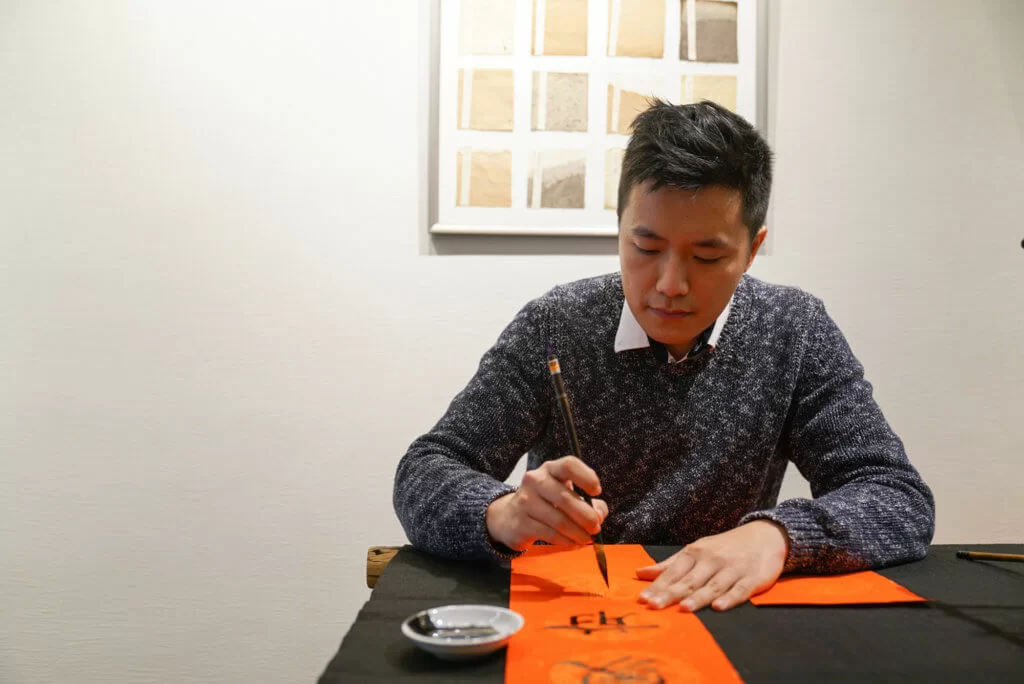
臨近新歲,家家戶戶也會在門前貼上各式賀年揮春。大家可曾心動過想揮毫撥墨寫出自己專屬的揮春?即使大家如筆者打從小學後已把毛筆擱下,書法已見生疏,其實也可以嘗試發揮創意,以畫揉合書法,寫出輕易上手的可愛「福豬揮春」。
準備好紙筆墨,就可安坐在案前,跟着影片示範動起筆來!明周今天請來三屆全港書法公開賽冠軍陳家浚(Sam),即席揮毫「福豬揮春」。拿起筆先畫上福字的框框,這部分的筆畫不多,容易掌握。「而寫田字的框框時要畫得圓潤點,就會更像一隻肥豬。然後,加上豬鼻、兩隻眼、兩隻耳。還有不忘加上牠的特點,畫上腳及尾巴,就完成了!」
Sam還額外給了三個小錦囊予「揮春新手」,好讓大家能寫得更得心應手。「第一,新買的筆要用清水浸十至二十分鐘,令毛筆尖端的膠水化開,然後揮掉膠水,毛筆呈現散開的狀態是正常的。第二,點墨時要點得滿至滴墨,再慢慢減少墨汁,因為寫揮春要寫得有福氣就要寫得肥及粗。第三,寫字時不要因剛嘗試寫而怯,把字寫得幼,寫得粗才能看見字的氣勢及福氣。」除了創意十足的「福豬揮春」,Sam續道揮春其實有細分不同的書體,如北魏楷書、草書、篆書、隸書等。
自小學二年級學習寫書法的Sam,已有二十多年習字經驗,獲獎無數亦會開班教學。如此鍾情於書法,皆因他覺得寫書法時的狀態很忘我,「書法就像一種運動,寫字時要吊筆,整個人要跟着筆去活動,呼吸又要配合。寫書法時整個人感覺很順暢,寫完就像做完運動般的爽。」
以他的觀察,他覺得其實有不少香港人都喜歡書法,只是因為日常工作忙碌,很難固定每星期抽出時間學習。他認為坊間的書法班其實可用切合「香港打工仔」的模式教學,抽絲剝繭拆解出書體的核心,把教學簡易化,讓參加者可以在個半小時到兩小時的課堂中成功寫到一篇書法,從成功感中逐步培養興趣。說罷,他繼續揮筆寫出「豬事順利」、「豬事大吉」、「大豬大利」等的揮春,祝賀大家新一年事事如意!